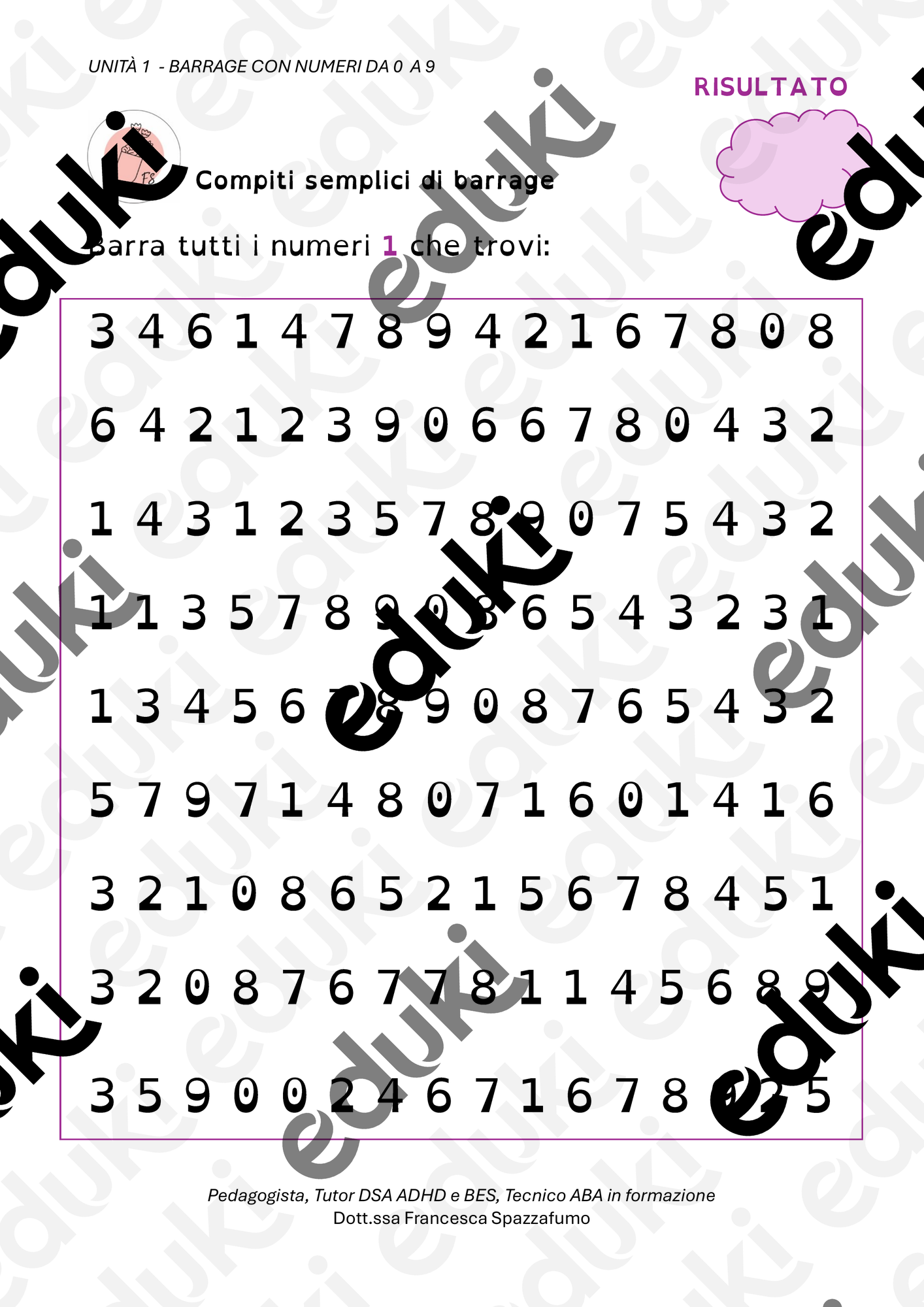
Esercizi - Barriage numeri da 0 a 9 con font DYSLEXIA - francesca_pedagogista - Pagina di copertina
Breve descrizione dell’attività:
attività educativa pensata per aiutare i bambini a riconoscere i numeri da 0 a 9, utilizzando il font DYSLEXIA, appositamente progettato per facilitare la lettura. stimola le abilità cognitive, migliorano l’attenzione visiva e sviluppano una maggiore familiarità con i numeri, il tutto in un ambiente inclusivo e divertente.
Barriage numeri da 0 a 9 con font DYSLEXIA